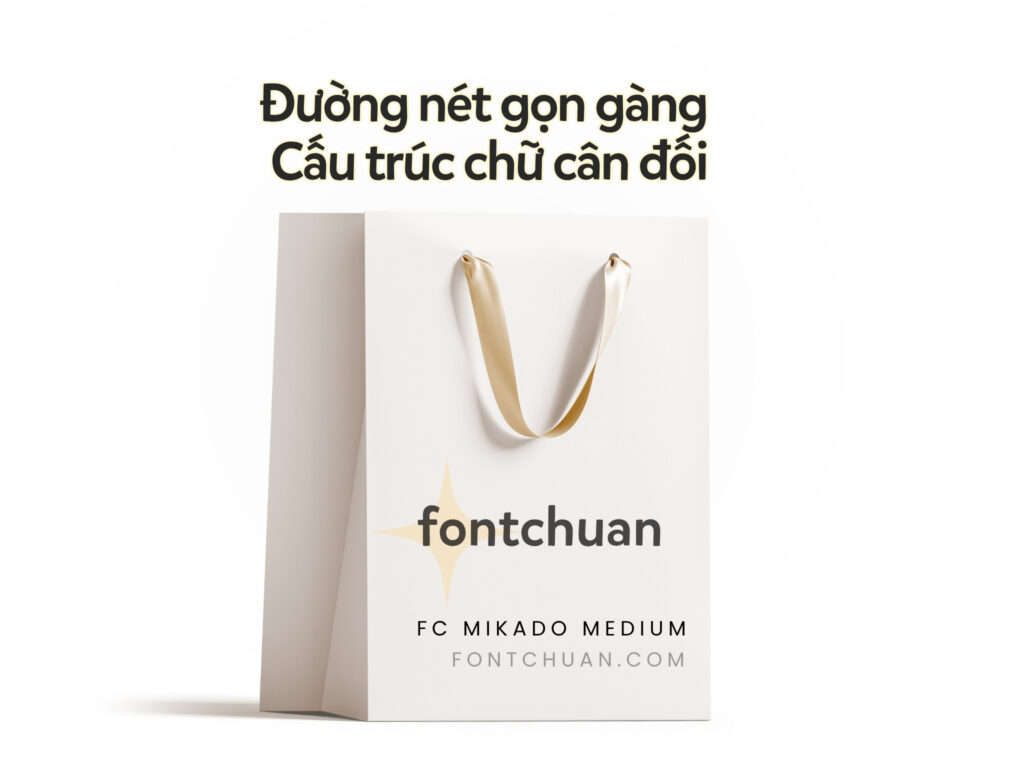
Font Mikado là một kiểu chữ sans-serif hình học với các góc bo tròn nhẹ nhàng, được thiết kế bởi Hannes von Döhren và phát hành bởi HVD Fonts vào năm 2013. Với thiết kế thân thiện và dễ đọc, bộ font này bao gồm 12 kiểu chữ, từ Light đến Ultra, cùng với các phiên bản nghiêng tương ứng, đáp ứng đa dạng nhu cầu sử dụng.
Về đặc điểm thiết kế, Mikado sở hữu các đường nét gọn gàng, cấu trúc chữ cân đối và độ tương phản thấp, tạo nên sự rõ ràng và dễ đọc ở cả kích thước nhỏ và lớn. Font này phù hợp cho nhiều ứng dụng như thiết kế giao diện người dùng, in ấn, thiết kế logo và các ấn phẩm truyền thông khác. Mang lại cảm giác vui tươi và ấm áp, Mikado còn có thể được sáng tạo thành font chữ Trung Thu, giúp thiết kế thiệp chúc mừng, poster sự kiện hay ấn phẩm mùa lễ hội trở nên gần gũi, sinh động và mang đậm không khí đoàn viên. Các ngành nghề như quảng cáo, giáo dục, công nghệ và bất động sản có thể tận dụng Mikado để tạo ra những sản phẩm ấn tượng và chuyên nghiệp.